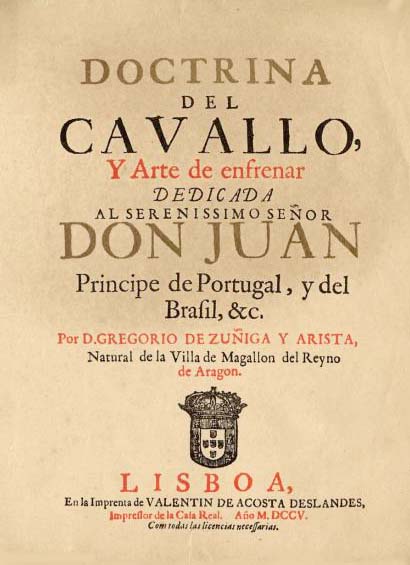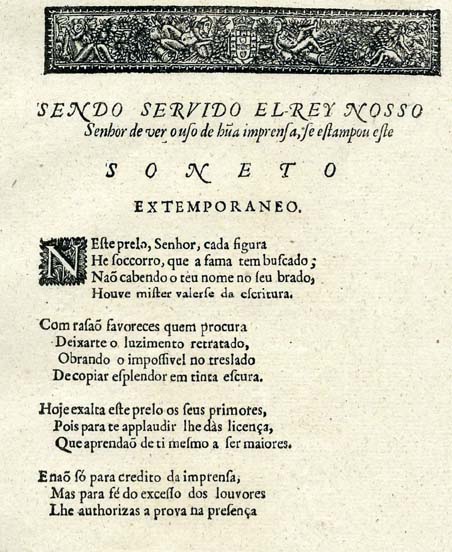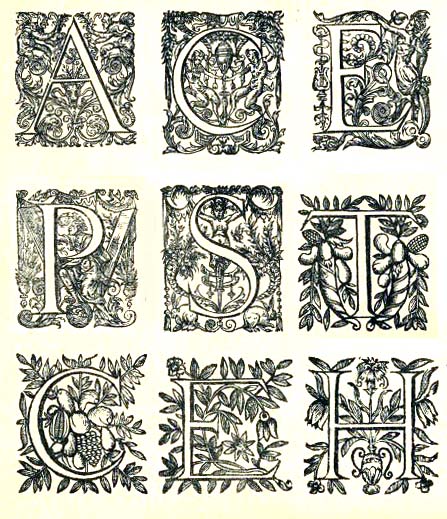
Miguel Deslandes (- 1703)Os Deslandes foram Impressores de Sua Majestade nos séculos XVII e XVIIIMiguel Deslandes (Thouars, Poitou, França (?) - Lisboa, 1703) foi um tipógrafo francês, naturalizado português em 1604. Ficaram famosos as suas vinhetas e floreados, gravuras em cobre. Miguel Deslandes intalou-se em Portugal em 1669. Casado com a filha do impressor, livreiro e editor Jean de la Coste (João da Costa), também estabelecido em Portugal, Deslandes herdou do sogro o material tipográfico com que imprimiu muitos livros em português, latim, espanhol francês e italiano. Jean de la Coste, por sua vez, tinha adquirido o material do tipógrafo Augustin Courbé. Por despacho de 1648, Deslandes naturaliza-se português para poder usufruir dos direitos de cidadania dos naturais do reino. Em 1687, depois da morte de António Craesbeeck de Melo, é nomeado «Impressor real». Com a sua morte em 1703 sucede-lhe, na direcção da régia oficina, o seu segundo filho Valentim da Costa Deslandes. Valentim da Costa Deslandes continuou o trabalho do pai, mantendo a tipografia que este iniciara,